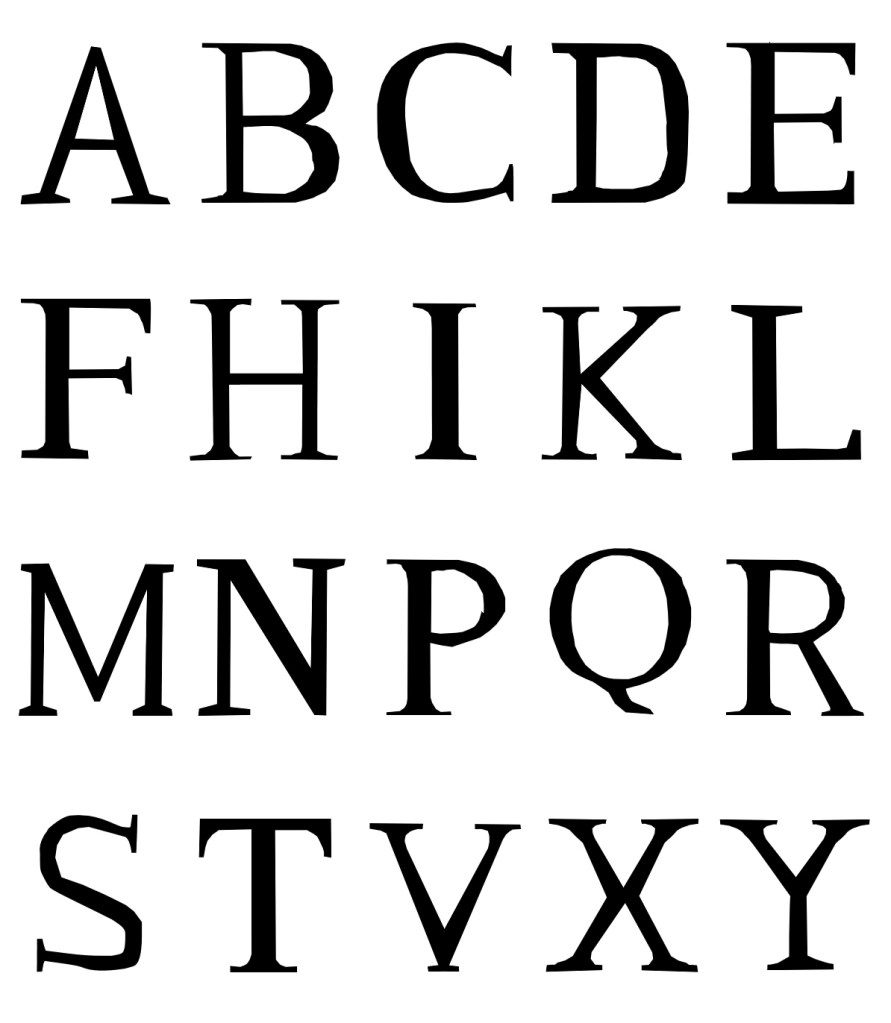
En 20 signes principaux, voici l’alphabet le plus connu dans le monde, non parce qu’il est la forme d’écriture la plus utilisée nativement, mais simplement parce qu’étant la source des langues véhiculaires Européennes les plus utilisées pour la communication de la plupart des locuteurs Planétaire. On observe d’ailleurs que cela date d’un effort ancestral de colonisation militaire et économique, qui fut en son temps entrepris et longuement développé par la République Romaine qui adopta l’écrit des Latins pour en faire le mode chéri de l’Impérium.
Des versions Latines
Les Romains, utilisateurs et diffuseurs assidus du latin, ont connu trois époques alphabétiques. L’écriture Latine d’aujourd’hui est celle qu’ils ont laissée après l’avoir figée vers l’an + 300 de notre ère. Bicamérale et lapidaire, elle possède 26 signes principaux.
Bicamérale désigne les deux aspects d’une écriture présentant les mêmes lettres sous deux formats différents, l’un, les capitales, utilisées pour manifester de la grandeur ou un début de phrase ou d’initiales et les autres, dites minuscules utilisées pour les textes courants .
« Lapidaire » vient du nom des graveurs et tailleurs de pierres et par usage une écriture tracée, pour ses capitales, au moyen de lignes, droites ou courbes les plus directes possibles.
Écrire et Construire.
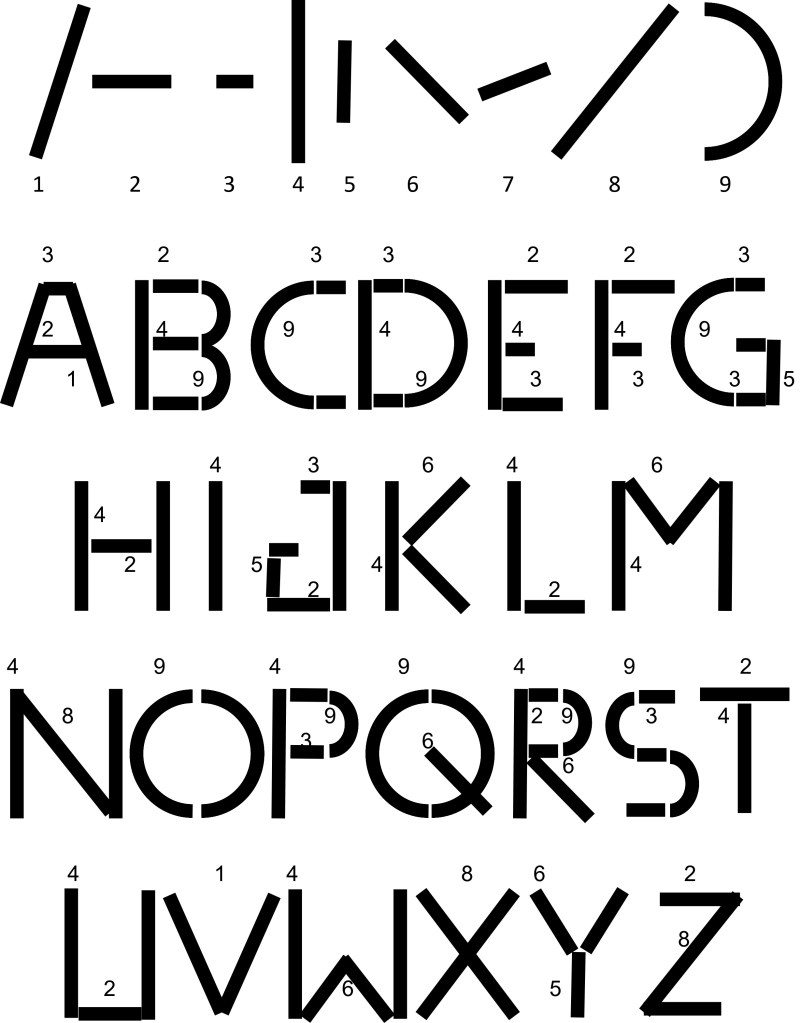
Avec quelques signes, il est possible de transmettre une chose fondamentale telle que le nom du bâtiment, généralement imposant et spécialisé, devant lequel nous nous trouvons pour exercer l’une ou l’autre des activités favorites du peuple, depuis l’écoute bienveillante des édiles corrompus à l’observation du massacre d’innocents. Les frontons vont accueillir quelques mots, une phrase de dédicace et une date. Une analogie directe existe entre la construction d’un ouvrage en pierres et celle des lettres, les capitales tout au moins, qui authentifient le sérieux et l’importance de l’édifice.
Nous ferons appel à des professionnels pour réaliser un mur dans un cas et une gravure dans l’autre. Ils vont se servir d’outils proches, burins et marteaux et tenter de livrer un résultat parfait.
Les défis dans l’exécution d’un bon travail sont proches : plus le matériau utilisé est beau et plus il a de chance d’être difficile à travailler, dur à tailler ou graver, il sera cassant et sujet aux fissures.
Le graveur de pierre, depuis l’aube de l’expression monumentale d’Egypte jusqu’à notre époque, est un artisan compétent dont les méthodes et arts ont peu changé depuis 5 000 ans.
Ce qui en fait l’un des plus vieux métiers du monde, de ceux qui sont respectés dans toutes les confréries de bâtisseurs, car on n’a rien trouvé de plus durable pour dédicacer une construction que de la parachever de quelques traits de gouge parfaitement tracés.
Les éléments de bases sont toujours les mêmes, des traits verticaux, horizontaux et biais et quelques arrondis, ce qui permet de créer l’ensemble des lettres utiles avec une grande économie d’outils et de gestes.
Le graveur commence par une petite taille en biseau, par laquelle il attaquera la pierre avant d’élargir peu à peu en s’assurant de ne pas fendre en fin de tracé. Ce petit trait caractéristique est repris depuis l’aube de l’écriture pour les polices de caractères « avec Sérif ».
Avec l’avènement de supports plus souples, requérant des outils plus légers, ces petits appendices furent interprétés comme des attaques ou relevés de pinceaux, ce qui est moins violent.
Un dérapage de plume ou de brosse provoque moins de conséquences douloureuses, les tâches faisant moins mal que les coups de gouges, sauf à l’amour propre.
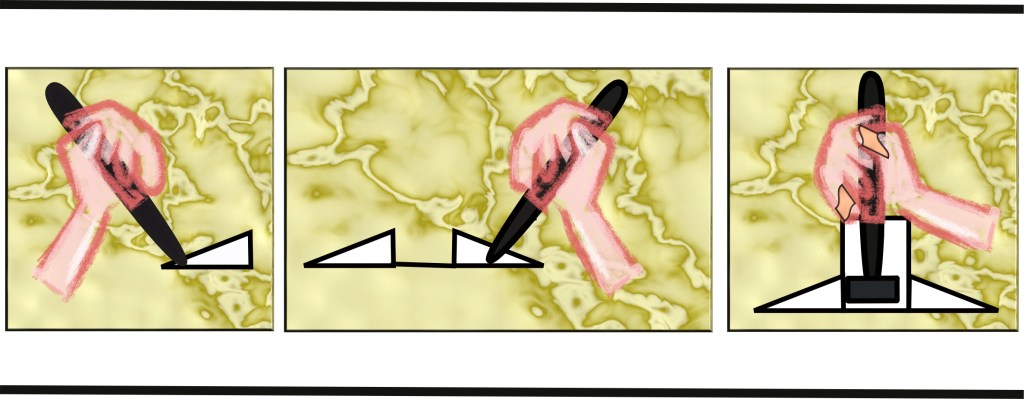
Pas de Jules avant + 300 !
On trouve la trace d’un Caivs Ivlivs Caesar, dans les « commentaires sur la guerre des Gaules ». Il se donne le premier rôle, ce qui est parfaitement son droit car il écrit à la première personne, avec 23 lettres seulement !
Bien avant l’illustre Ivlivs, l’alphabet Latin est dit archaïque, c’est la version 1 qui fut établie comme écriture unifiée des citoyens Romains et de leurs nombreux ralliés, vers – 650.
Entre – 350 et + 300, nous avons affaire au Latin classique. Cette version 2 ne comportait que 23 lettres, le J, le U et le W étaient absents. Le Latin archaïque comporte 20 lettres, ce qui est peu. Le G, le O et le Z ne figurent pas dans la liste.
Le latin des origines n’était pas gravé
Dans les textes les plus anciens, nous trouvons des graphies et des orientations de lettres particulières.
Les branches du F sont inclinées, P ressemble à une potence, ce qui deviendra un R ne dispose que d’un embryon de ligne de retour. Enfin, ce que nous identifions comme un C, est pivoté en coupole.
Ces différences sont limitées. Avec un peu de concentration, les textes anciens nous sont visuellement familiers, restant lisibles et éventuellement compréhensibles par les latinistes.
Les différences entre le Latin Archaïque et le Latin Classique sont très sont limitées. Avec un peu de concentration, les textes anciens, majoritairement sur papiers ou papyrus, nous sont visuellement familiers, restant lisibles et éventuellement compréhensibles par les latinistes.
Les interactions avec les autres alphabets
Cette suite de caractères crée par les Latins a adopté comme expression unique par les Romains, sans doute à l’avènement de la République, suite à la désertion du dernier Roi de Rome Étrusque.
La diffusion s’est faite largement au grès des conquêtes et des ralliements, au point de supplanter les Phéniciens. par contre, l’alphabet Grec a réussi à survivre réussissant même à imposer certaines de ces graphies.